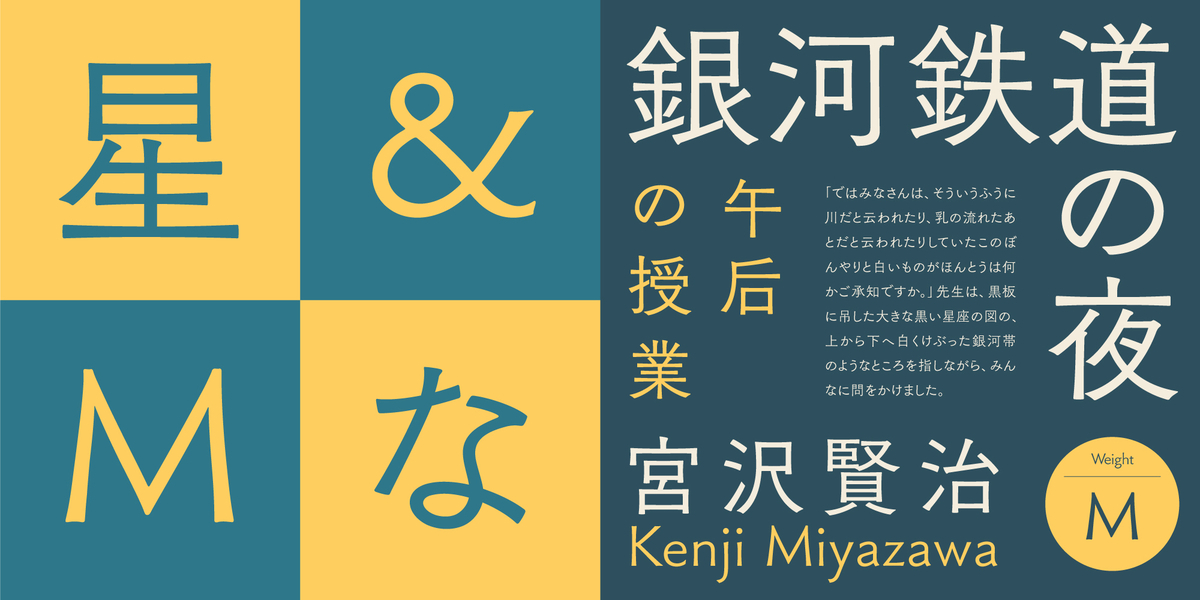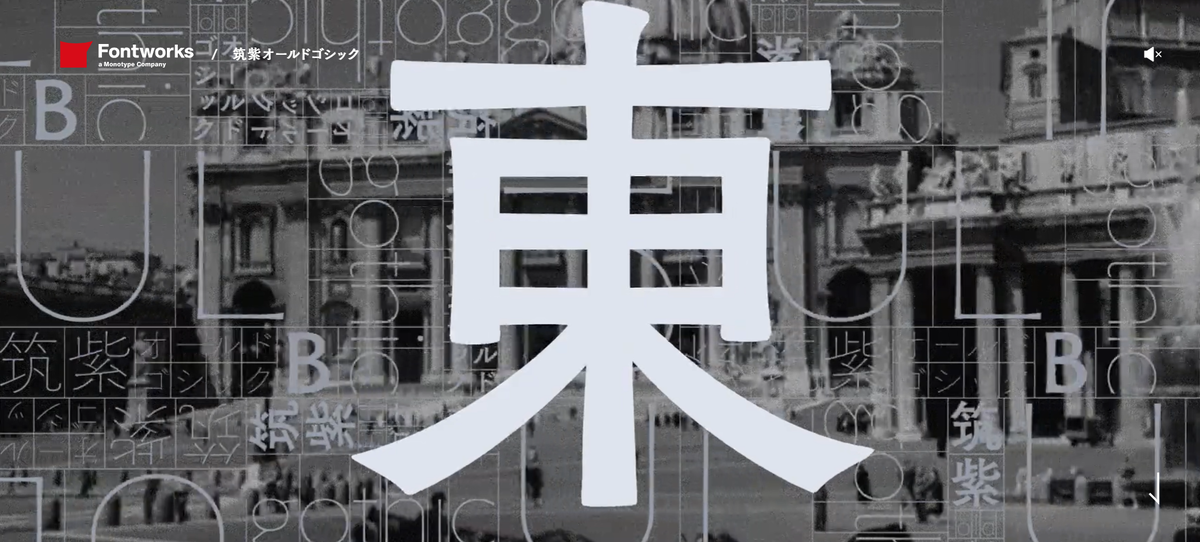
フォントワークスが人気フォント「筑紫オールドゴシック」の新4ウエイトを追加
フォントワークス株式会社は、2024年9月5日に、人気書体「筑紫オールドゴシック」に4つの新ウエイトを追加したことを発表した。
筑紫オールドゴシック
「筑紫オールドゴシック」は、フォントワークスの書体デザインディレクターである藤田重信氏が2014年に、金属活字時代に存在していたかのようなゴシック体をイメージしながら設計した、全く新しい書体。
漢字や仮名の引き締まったふところ、伸びやかなはらい、筆の名残りを感じる豊かな抑揚が、凜々しく言葉を語る。
今回新たにに追加されたのは「R(レギュラー)/M(ミディアム)/D(デミボールド)/E(エクストラボールド)」の4ウエイトで本文にも使いやすく、表現の幅が広がる。
「筑紫オールドゴシック」は今回の追加で全部で6ウエイトのファミリーとなった。
▼筑紫オールドゴシック R(レギュラー)
▼筑紫オールドゴシック M(ミディアム)
「R」の次に細い書体となる。本文にお勧めの書体。
▼筑紫オールドゴシック D(デミボールド)
▼筑紫オールドゴシック E(エクストラボールド)